字体现在不仅仅是一种文化,更是一种审美,甚至也可以说,字体是一种吸引眼球的方式。当我们制作横幅或者广告牌时,除了上面的图画,大概就只能靠字体来抓住消费者的心了。可能很多人并不明白其中的道理,但字体的确可以吸引人。下面将为大家介绍时尚字体设计相关内容。
随着社会的进步,人们的审美也发生了改变,经典字体不能满足人们的审美需求,所以时尚字体孕育而生。很多人都想为自己设计一种专属的时尚字体,但是奈于不了解,一直都无法实现这个想法。其实时尚字体设计的方法有很多,像是叠加法、俏皮设计法、共用法、分解结构法等字体广告设计方法,都是比较容易掌握的,可以帮助大家设计出自己想要的字体。
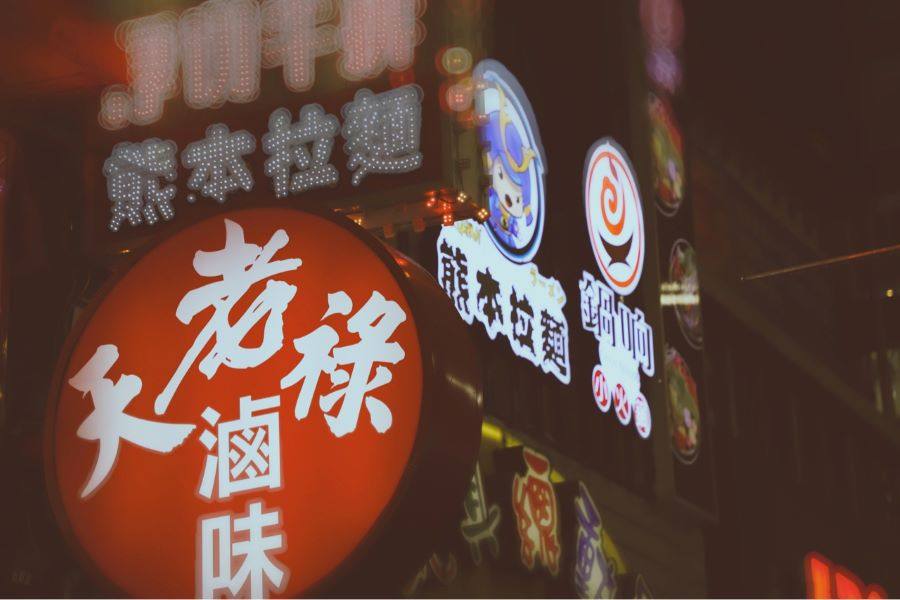
时尚字体设计的最大特点就是字体的笔画和结构。不用于常规的宋体、黑体、楷体,在时尚字体设计中,字体的笔画得到了很大的改变,有的字体笔画被进行了叠加,也有的字体笔画被进行了分解,总之,时尚字体设计就是让字体呈现出一种创意感。
时尚字体设计可以适用于广告牌制作和海报制作,尤其是明星的海报广告中,经常会用到时尚创意字体,因为时尚字体比较符合现代人的审美,也比较容易被接受。
以上就是为大家介绍的关于时尚字体设计的具体内容,时尚字体设计应该是最受年轻人喜欢的字体,如果大家感兴趣的话,可以深入的了解一下。